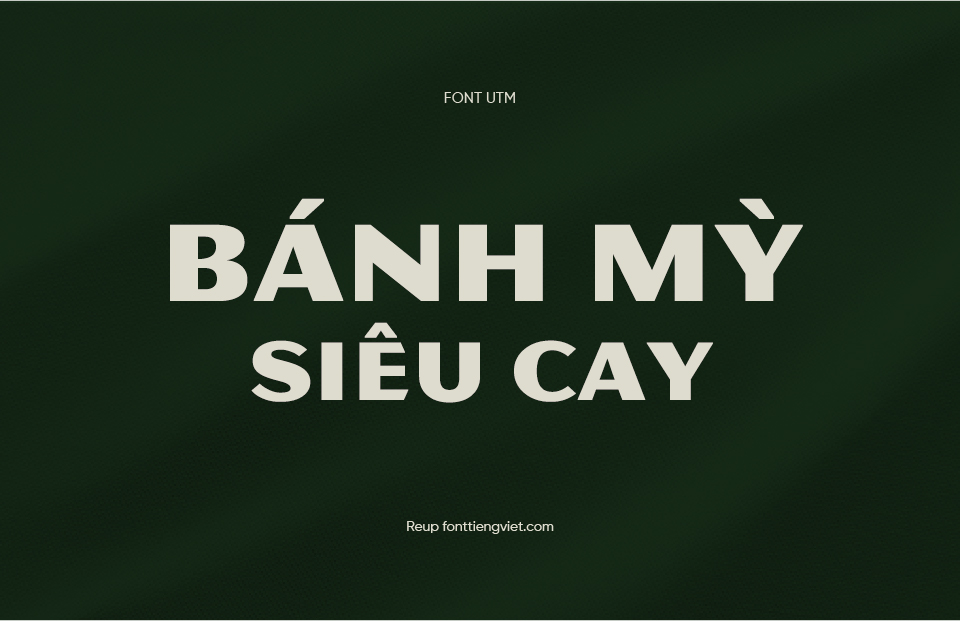
Tải Ngay Font Việt hóa UTM Magnesium Đẹp Nhất Cho Thiết Kế Đồ Họa
Font Việt hóa UTM Magnesium là một trong những bộ phông chữ độc đáo được giới thiết kế tại Việt Nam cực kỳ ưa chuộng nhờ phong cách hiện đại và mạnh mẽ. Nếu bạn đang tìm kiếm một Font Chữ có khả năng tạo điểm nhấn thị giác ấn tượng cho các dự án sáng tạo, thì đây chính là lựa chọn không thể bỏ qua. Bộ font này đã được tinh chỉnh kỹ lưỡng về dấu tiếng Việt, đảm bảo sự đồng nhất và mượt mà khi soạn thảo văn bản. Với đường nét sắc sảo, UTM Magnesium giúp các bài thuyết trình hay ấn phẩm truyền thông của học sinh và nhà trường trở nên chuyên nghiệp hơn bao giờ hết.
Đặc điểm nổi bật của Font Việt hóa UTM Magnesium
Thiết kế hiện đại và linh hoạt
Đặc trưng của Font Việt hóa UTM Magnesium nằm ở cấu trúc hình khối vững chãi nhưng không kém phần thanh thoát. Các nét chữ được thiết kế cân đối, giúp người xem dễ dàng tiếp nhận thông tin ngay cả ở khoảng cách xa. Điều này làm cho font chữ trở nên lý tưởng cho các loại tiêu đề báo tường, banner sự kiện trường học hoặc bìa sách giáo khoa. Sự kết hợp giữa phong cách cổ điển và hơi hướng tương lai giúp bộ font này thích nghi tốt với nhiều bối cảnh khác nhau.
Tối ưu hóa cho người dùng Việt Nam
Vì đã được Việt hóa hoàn chỉnh, Font Việt hóa UTM Magnesium khắc phục hoàn toàn lỗi nhảy chữ hoặc sai dấu phổ biến ở các font quốc tế. Người dùng có thể tự tin sử dụng trên các phần mềm phổ biến như Photoshop, Canva hay Microsoft Word. Độ tương phản giữa các nét thanh và nét đậm được tính toán chi tiết, mang lại cảm giác dễ chịu cho mắt và tăng tính thẩm mỹ cho toàn bộ bố cục thiết kế của bạn.